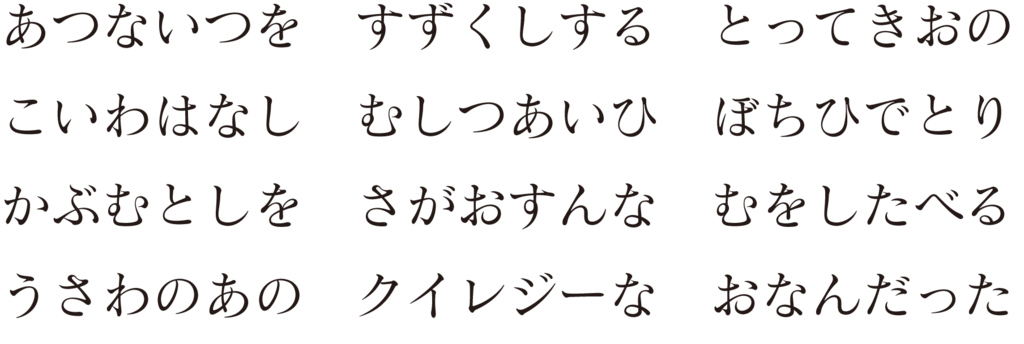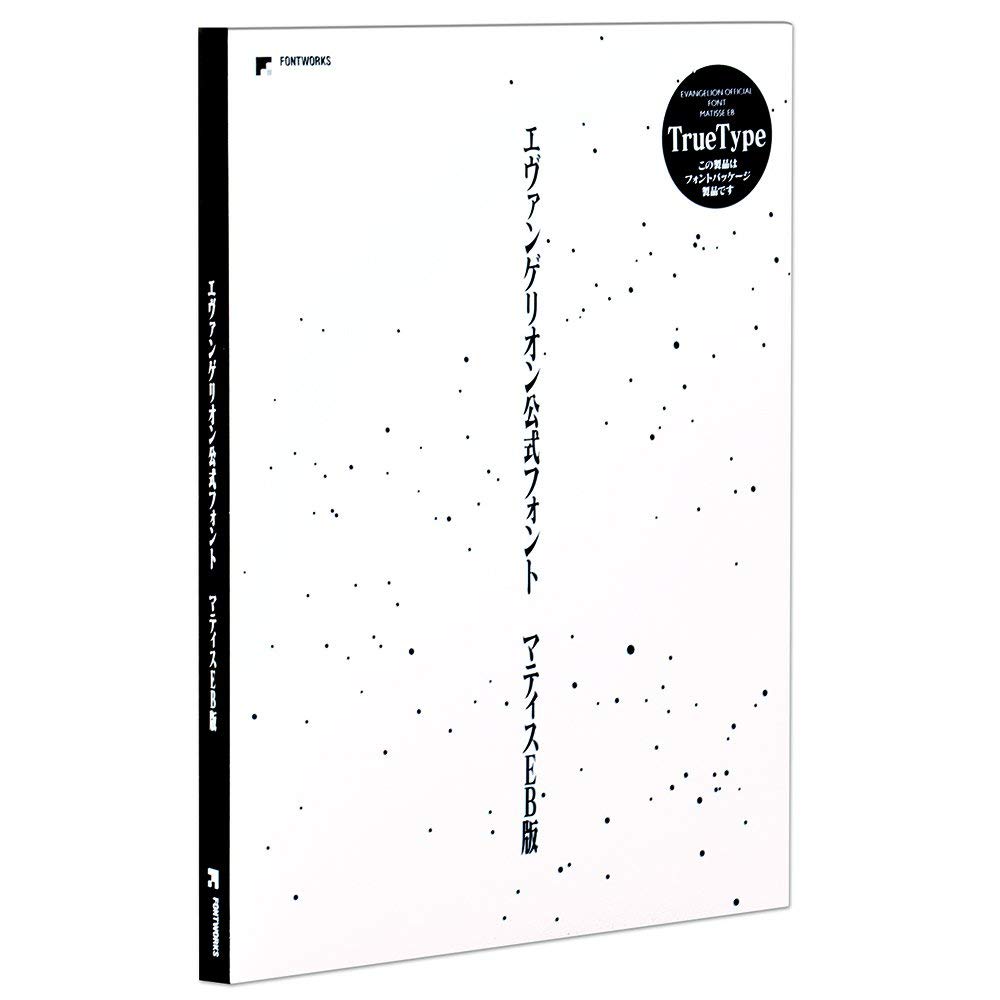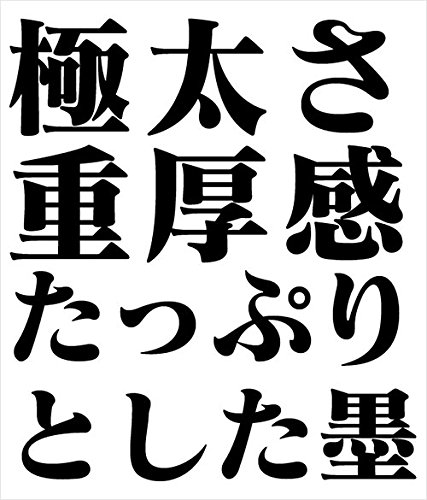
マティス
フォントワークスの明朝体。「漢字」と「かな」のバランスが良く、文字組みしたときに最大限の読みやすさを発揮する。デザインはロダンを手がけた佐藤俊泰氏。
マティスのウェイトEBは、新世紀エヴァンゲリオンのサブタイトルに使われて有名で「エヴァフォント」とも呼ばれている。
「フォントワークス エヴァンゲリオン公式フォント マティスEB Truetype版」には新世紀エヴァンゲリオンのTVシリーズで使用された「EVA-マティス-クラシック」と新劇場版で使用された「EVA-マティス-スタンダード」を収録。